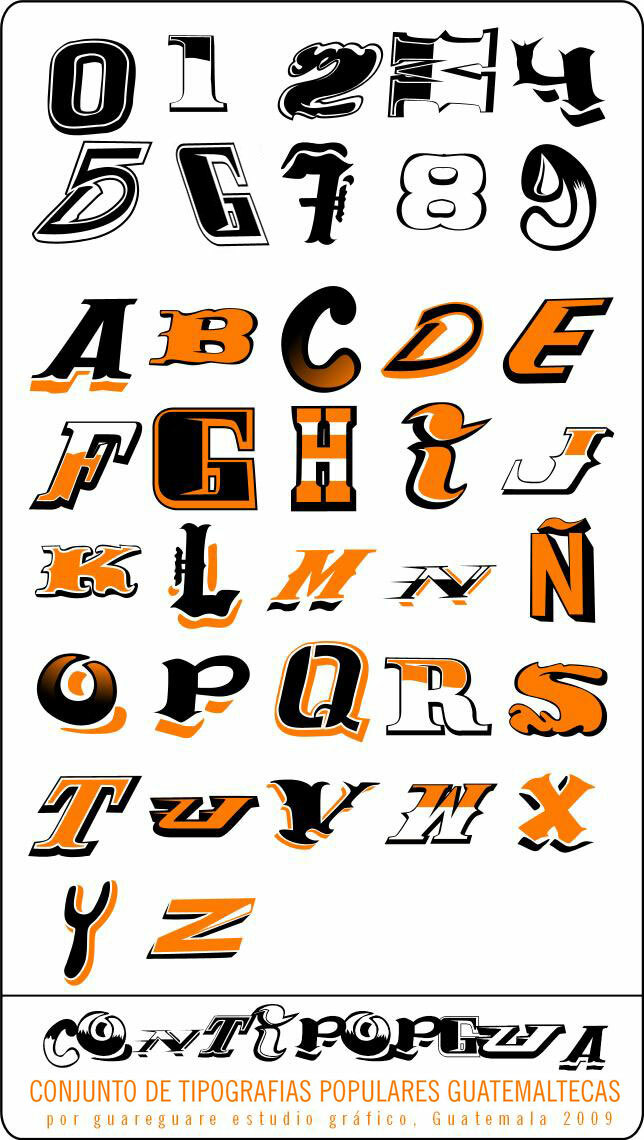
Conjunto de Tipografias Populares Guatemaltecas
Group of guatemalan popular tipography; currently used in the streets, buses, publicity, etc. as part of our popular culture. Designed by guareguare graphic studio.
Conjunto de tipografia popular guatemalteca; habitualmente usada en las calles, buses, publicidad, etc. como parte de nuestra cultura popular. Diseada por guareguare estudio grfico.